陈先行的《古籍善本》书影辨识版刻字体是鉴定版本的第一要务近年来,有人将版本学界的学者分为鉴赏派与考订派,这恐怕是受到清代洪亮吉将藏书家分为五等说法的影响。关于洪氏的说法正确与否,我们将另行讨论。我认为无论什么派,都必须以掌握鉴定版本的本领为前提。鉴定版本固然不能仅仅根据版刻形制,往往还要从版本源流、书的内容等方面作相关考订。但根据版刻形制做出大致判断是鉴定版本的首要步骤。而书一开卷,最夺人眼球的就是字体,因此辨识字体乃鉴定版本第一要紧之事。仅以字体鉴定版本,或许不够准确,但倘若不辨字体而说鉴定版本,则是无稽之谈。前辈们所谓“观风望气”,以我的理解,主要也是就字体而言。如果不辨字体,只认牌记、避讳字或刻工等,那么很可能把明清仿宋、翻宋刻本误当宋刻本。
宋版或有佛经采用苏东坡行楷者,如上海图书馆收藏的北宋崇宁刻本《妙法莲华经》,一式苏体小字,极为神似。但总体而言,宋代刻书者推崇唐楷,较多采用欧阳洵、颜真卿、柳公权字体,这固然是三家楷书登峰造极的影响所致,可能也是宋代缺乏与之媲美的楷书大家的缘故。前人就所见存世宋本(主要是南宋刻本),总结出其字体具有浙欧、蜀颜、闽柳的地域风格,相对而言是符合实际情况的。因此,必须对欧、颜、柳之书体特点,相应对宋代浙、蜀、闽三个最有影响的刻书中心的字体有一个大概了解。
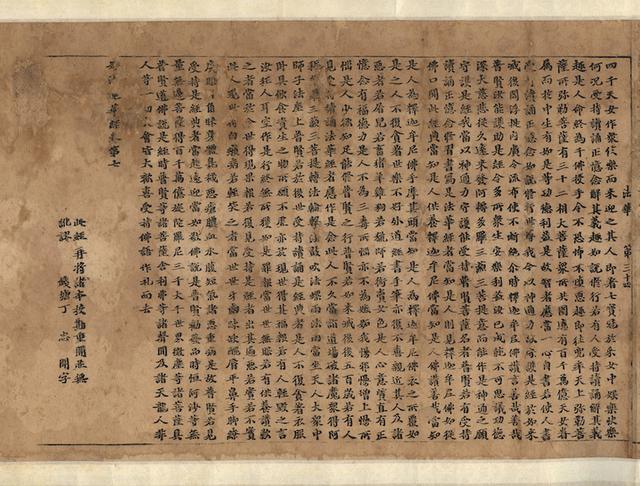
上海图书馆收藏的北宋崇宁刻本《妙法莲华经》书影先说欧字。欧阳洵(557—641)是由隋入唐的书法大家,其楷书严谨而不刻版,峭劲而不姿媚。代表作有《九成宫醴泉铭》《化度寺塔铭》《皇甫诞碑》《虞恭公碑》等。版本学家们所谓“字体方整”,多指南宋浙刻欧字本。在我看来,辨别宋版是否欧字,观其弯钩处最为分明,其弯钩曲圆较长,外方内圆,即所谓欧字融隶于楷的鲜明特点所在。
欧阳询《九成宫醴泉铭》拓本
南宋浙刻欧字本《武经龟鉴》书影次说颜字。颜真卿(709—785)是盛唐时期的书法大家,作品多且富于变化。其43岁时所作的《多宝塔碑》结体严密,端庄秀丽,但不是颜书典型。63岁作的《麻姑仙坛记》,以圆代方,肥瘦匀称,庄严大气,被称为颜书之冠,也是其代表之作。过去有的版本家描述宋版字体有所谓“蚕头燕尾”之说,应当是指南宋蜀刻颜字本。但“蚕头燕尾”是否为颜字特点,在宋代就有不同看法(参见米芾《海岳名言》及《宣和书谱·颜真卿》)。若就蜀刻本的面貌而言,其起笔並无“蚕头”现象。我认为辩识宋版颜字可注意两个特征,一是其重点的竖划略呈圆弧状;另一就是捺脚收笔出锋处分成叉式如燕尾状,今存《杭州西湖昭庆寺结莲社集》《妙法莲华经入注》等北宋浙刻本最为典型,而南宋蜀刻本之燕尾状已不明显,但意蕴犹在。
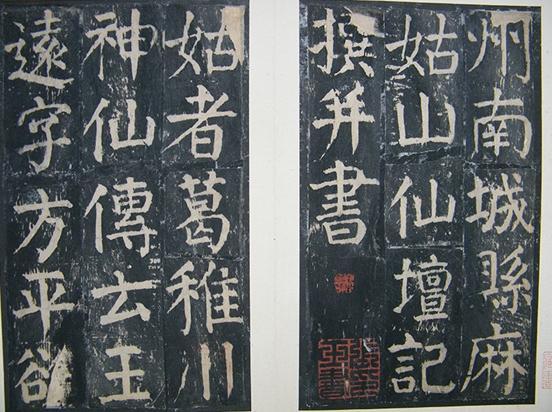
颜真卿《麻姑仙坛记》拓本
《杭州西湖昭庆寺结莲社集》
南宋蜀刻颜字本《春秋经传集解》书影再说柳字。柳公权(778—865)是唐代最后一个书法大家,代表作有《金刚经》《神策军碑》《玄秘塔碑》等。他的字吸收了欧的严谨、颜的遒劲,点划挺秀,均匀瘦硬,自成一体。版本家们所谓“字体隽丽,锋棱峭厉”,就是指南宋建刻柳字本。我觉得柳字取法颜字更多,尤与《多宝塔碑》相近;甚至偶尔还有颜字“燕尾”痕迹,所以要细加分辨。鉴别宋版是否柳字,就要抓住挺秀、瘦硬这两个特征,这是与颜体颇为鲜明的区别。
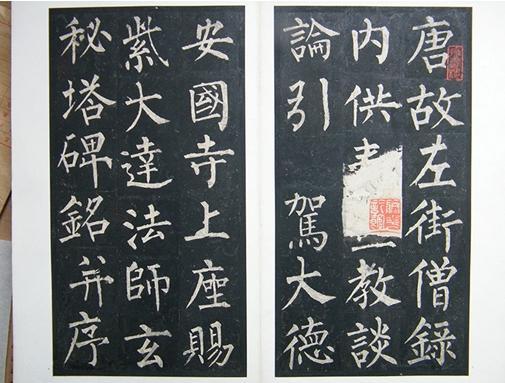
柳公权《玄秘塔碑》拓本
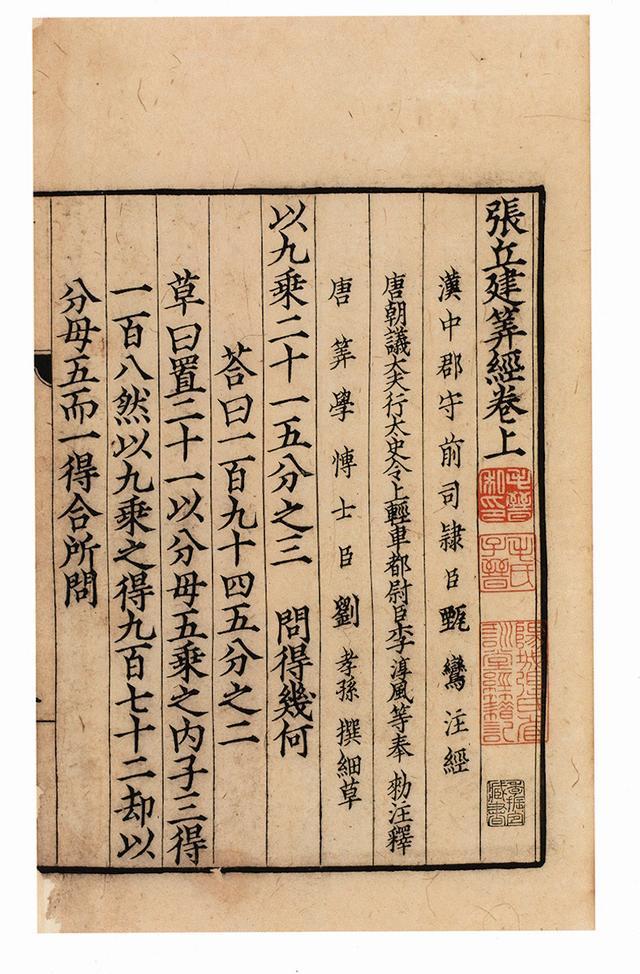
南宋建刻柳字本《张丘建筭经》书影碑刻虽是书法家手书上石,但一经凿刻,与墨迹多少会有出入;而拓本有早晚,拓手的技术有优劣,难免又有走样。至于雕版,字体虽曰仿自欧、颜、柳云云,其实已经是宋代写工与刻工的作品,何况其水平既有高低,刊刻遂有精粗不同,所以我们看到的版本字体大多与书法家的原迹存在差异,只能去领会其有无某一书法家的特点与意蕴,而不能刻板地与碑帖硬作比对。如果你所见的碑版拓本是一个拙劣的翻刻本,那更会跌入云里雾里。不过,宋本字体有一个共同的特点,即多以露锋或半藏锋起笔,因而观其横划,每呈起笔轻落笔重之状。该特点于南宋福建刻本尤为明显,故与当地元代及明代前期书坊刻本的字体不难区别。元代推崇趙孟书法,风气之盛,于刻本中多所流行。今藏南京图书馆的元至正刻本《师子林天如和尚语录》,堪称元刻赵体字本之白眉。
南京图书馆收藏的元至正刻本《师子林天如和尚语录》书影
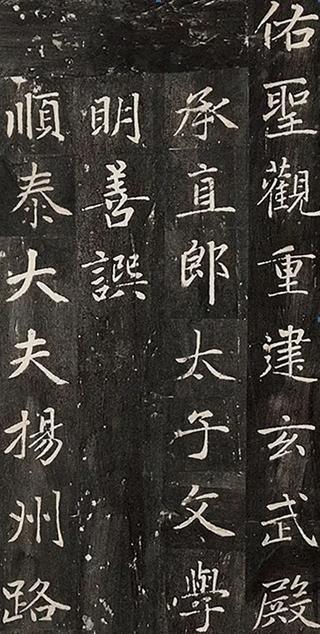
故宫博物院藏赵孟《佑圣观重建玄武殿碑》拓本但须注意:赵孟书体从唐人李邕书法演化而来,故学赵字要结合研习李字,《李思训碑》《麓山寺碑》是李氏代表之作,其书体在元刻本中也每有反映。如元刻本《诗童子问》,正文为福建书坊习用之匠体字,若读者以赵孟书体去比对,那是无法作出判断的。
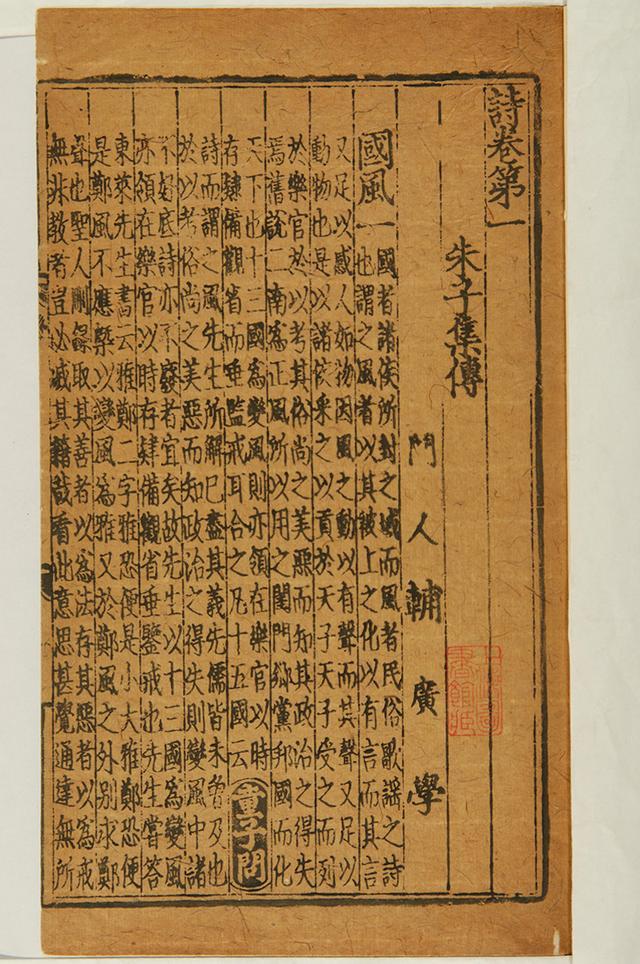
元至正四年(1344)崇化余志安勤有堂刻本《诗童子问》其实鉴定版本不仅要看正文字体,也要留意序跋文字体,因为序跋文常常是作者手书上版,或是请名家代为书写,其字体往往更能体现时代风气。而该本《诗童子问》胡一中之序文的书法就极具李邕书体面目。至于有人将元代甚至明代前期福建书坊刻本习用的字体也一股脑儿说成是赵体字,这实在是一种误导,须引起注意。这种字体虽然根源唐楷,由建刻宋本之字体化出,但于起、落笔特别强调,尤其是逆锋起笔,初始每呈圆钩状(圆钩状宋本偶然也有,多因运笔顺势自然形成,与元本刻意而为者不同),后来变为圆角或蚕头状,颇为夸张。至明代前期,它一直为福建刻书特别是书坊刻书所采用。然而,这种字体之流行,或者说这种版刻风格的形成,有一个渐变过程。元代初期的福建刻书,即便同一部书版,其字体并非皆呈如此面貌,建刻宋字尚占据一定版面,只是相较宋本字体偏软而已。迨至元代中期,宋本字体的遗意遂荡然无存,一式这种字体。但是,从元中期至明前期,这种字体也是有变化的,元中期时的字体尚具秀逸灵动之态,而元后期则略显板滞,至明前期则呈偏长而规整之匠字,了无生趣。当然,各时期所刻又有精粗高下之分,须细加比较,方能有所意会。
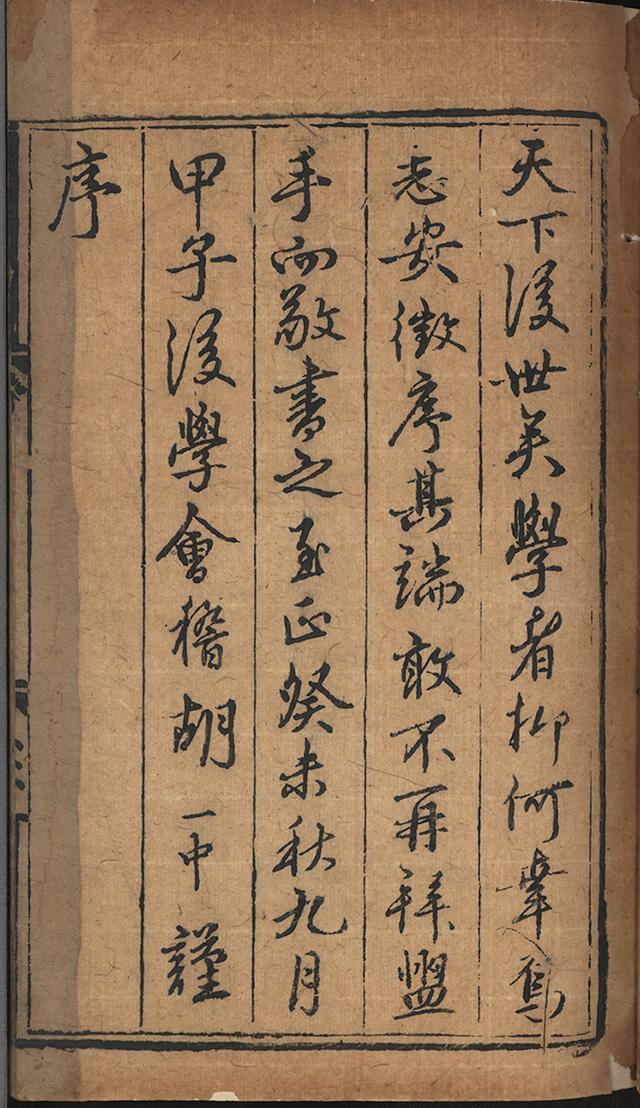
元至正三年癸未会稽胡一中序文明代刻书,总体上前期犹沿元代赵体字风格。正德、嘉靖间,以苏州地区为代表的仿宋刻本盛行。有人将这种仿宋刻本的字体称为“宋体字”,初学者未必理解,有必要辨析。“宋体字”在版本学上有两种含义:一是指宋版的字体,这其实是一种较为模糊的说法,因为宋版的字体多样,姿态不一。过去已有这样的说法,但仅限于内行的心领神会,外行则难以明白。另一则专指变化于明代正德、嘉靖,成型于隆庆、万历的仿宋字体。现存正德、嘉靖时期的仿宋刻本,大都仿欧体字,也就是说,当时至少有一批本子是直接根据宋代的浙刻欧字本仿刻,其上乘之作仅下宋本真面一等,于是又有“影宋刻本”之说。风气一旦形成,几乎成了正德后期至嘉靖间刻书的常用字体,即使非直接翻宋之本,亦不乏精品。后来为便于施刀,刻意突出起笔轻落笔重的特点,从而使字体变得规整划一,于是欧书神韵渐渐失去。
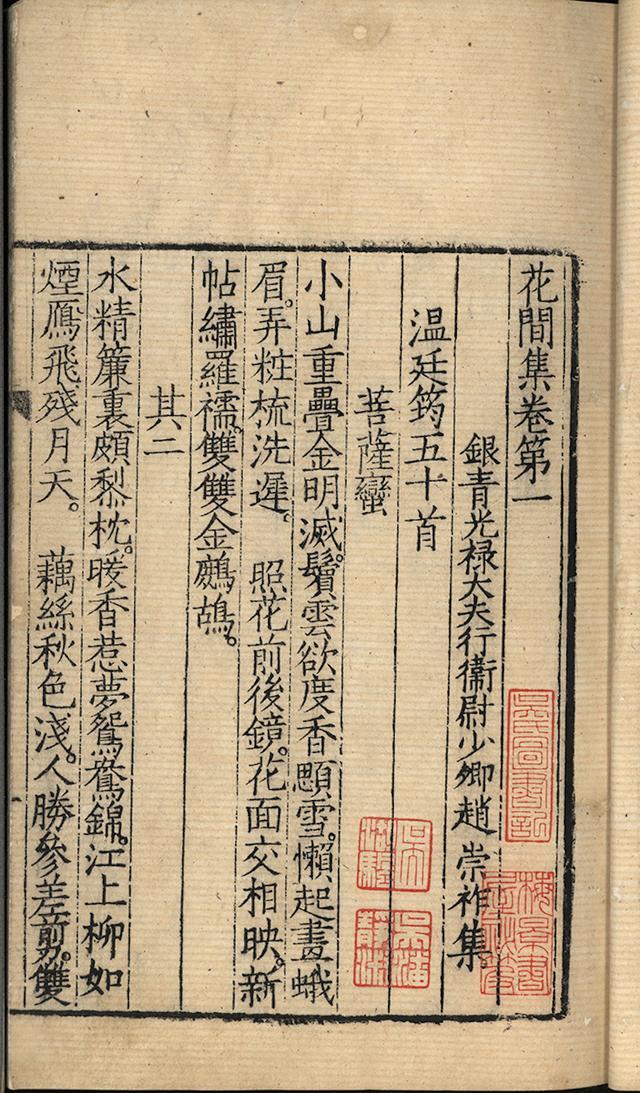
明正德十六年(1521)陆元大仿宋刻本《花间集》书影到了万历年代,这种字体又融入了颜体成分,演变成横细直粗的方体字(直粗就是颜体竖划之变异),尽管这种字体有长方肥瘦之多端变化,自是至今,一直被称为“仿宋体”,又称“宋体字”。这种字体并非突变而来,而是通过一定的变化发展。譬如嘉靖四年(1525)许宗鲁宜静书堂刻本《国语》,乃旧时书商撕去序文冒充宋本者。由于这个本子有些字的写法采用古字结构,而其字体点划与一般嘉靖本相似,要说不同之处,那就是含有颜体意味,显得丰腴,尤其是捺脚,特点突出。其实类似这种字体的本子并不少见,《天禄琳琅书目后编》或有误将明本作宋本者,就有类似字体。另有一个嘉靖十一年(1532)郏鼎刻本《汉隽》,则更为典型,其字除捺脚较硬外,基本就是颜体了。我认为这类本子的字体对万历宋体字的产生一定有影响,万历宋体字只是更强调了颜体成分从而异化成为一种新的字体。
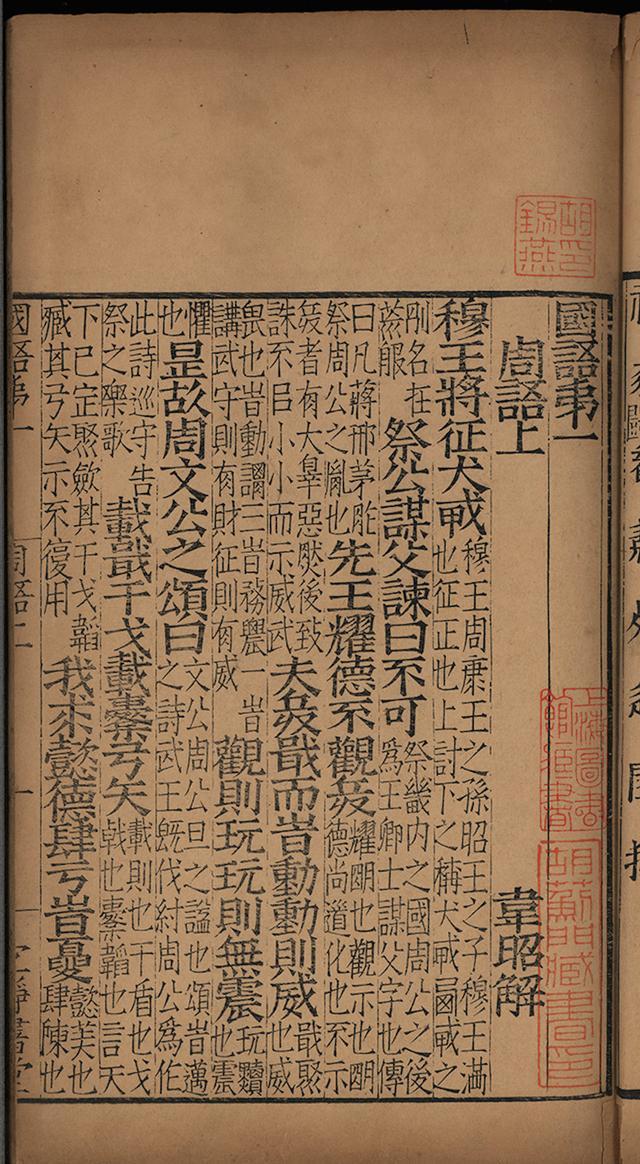
明嘉靖四年(1525)许宗鲁宜静书堂刻本《国语》书影有人以为万历字体直接仿自南宋后期浙江临安的书棚本,这并不确切,应当说是嘉靖仿刻本多少受到了书棚本的影响,故2006年惊现于市场的书棚本《南岳稿》,就被人误认为是明刻。书棚本字体虽笔划粗细较为匀称,细审仍为欧体,并无颜书意味,与万历宋体字迥不相侔。顺便指出,有的学者沿袭旧时某种偏见,每将万历这种宋体字轻慢地称为匠体,而无视其创造性,是有失偏颇的。这种字体在清康熙时代发展到顶峰,曩昔被藏书家称作康熙精刻本者,有不少即指该类隽美的宋体字本而不皆是软体字本。此外,这种字体又有软体字所无的大气肃穆,犹如榜书,非颜体不能呈现稳重而磅礴之势态,这也是其常被清代内府刊刻有关政治的书籍所采用的原因。
书棚本《南岳稿》
清康熙三十二年(1693)刻本《江村消夏录》书影虽然从明万历到有清一代刻书,多采用横细直粗的仿宋体,但字形有大小肥瘦之变化,刊刻有精粗高下之区别,须细加比较体会。譬如万历刻本字体大而肥,天启崇祯乃至康熙小而瘦,当然这是总体上相对而言。此外,在万历间,也出现楷书或行楷书体的写刻本,俗称“软体字本”。清康熙至道光间也出现不少写刻本,多出名家手笔,风格不一,非常精彩,如林佶写刻本《渔洋山人精华录》等。以上关于版刻字体,只是粗粗讲了一个大概,譬如宋代浙江、四川、福建以外地区刻书字体的特点,宋末元初、元末明初福建刻本的字体鉴定等等,皆有待深入研究。
康熙三十九年(1700)刻本《渔洋山人精华录》书影(本文来自澎湃新闻,更多原创资讯请下载“澎湃新闻”APP)